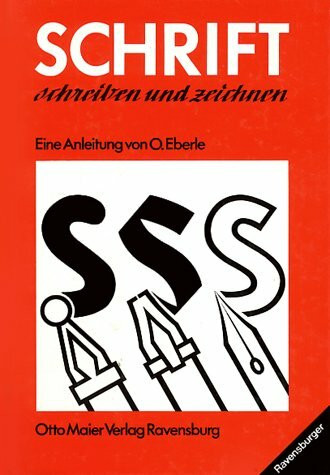
Schrift schreiben und zeichnen. Lehrgang zur Erlernung der verschiedenen Schriftarten
"Schrift schreiben und zeichnen. Lehrgang zur Erlernung der verschiedenen Schriftarten" von Ortwin Eberle ist ein umfassender Leitfaden, der sich an Personen richtet, die ihre Fähigkeiten im Schreiben und Zeichnen von Schriften verbessern möchten. Das Buch bietet eine strukturierte Einführung in verschiedene Schriftarten und vermittelt sowohl theoretische Grundlagen als auch praktische Übungen. Leser lernen, wie sie mit unterschiedlichen Werkzeugen und Techniken arbeiten können, um Buchstabenformen zu gestalten und individuelle Schriftstile zu entwickeln. Der Lehrgang ist didaktisch aufgebaut und eignet sich sowohl für Anfänger als auch für Fortgeschrittene, die ihre Kenntnisse vertiefen möchten. Dabei legt Eberle besonderen Wert auf Präzision und Kreativität im Gestaltungsprozess.